Come trovare e utilizzare i caratteri supportati dalla posta elettronica per il design e la leggibilità
Hai mai creato un'e-mail a caso e hai scelto il primo carattere che hai visto? Premi invio. Chiamalo buono per andare?
Quando si tratta di design dell'e-mail, la scelta del carattere può fare un'enorme differenza tra un abbonato che fa clic o va avanti. Non solo aiutano a rendere la tua email visivamente più accattivante, ma possono anche migliorare la leggibilità generale. L'aspetto, la disposizione e lo stile lavorano tutti insieme per creare una tipografia unica, che è dove la tua email può brillare.
Anche se non c'è niente di sbagliato nell'utilizzare i font tradizionali, come Arial o Times New Roman, per comunicare il tuo messaggio, esistono molti font unici supportati dalla posta elettronica che porteranno le tue campagne al livello successivo.
Se ti stai chiedendo come trovare e utilizzare i caratteri Web supportati dalle e-mail per dare il via alla tua campagna e-mail, siamo al tuo fianco! Diamo un'occhiata a come puoi migliorare il tuo coinvolgimento e la leggibilità utilizzando correttamente i caratteri web.
Cosa sono i caratteri web?
Prima di iniziare a essere creativo, devi conoscere la differenza tra i caratteri Web e quelli sicuri per il Web.
Font sicuri per il Web: è molto probabile che questi font si trovino in tutti i principali sistemi operativi e provider di posta elettronica e includono Arial, Verdana, Georgia, Times New Roman e Courier. I marchi continuano a usarli perché sono classici e renderanno correttamente su tutta la linea.
Font Web: appositamente progettati e concessi in licenza per i siti Web, i font Web non si trovano su tutti i dispositivi e sistemi operativi per impostazione predefinita. I caratteri Web includono Roboto e Open Sans.
Sebbene a volte potresti dover utilizzare i caratteri tradizionali, i caratteri Web consentono al designer una maggiore creatività per aiutare a trasmettere il messaggio e l'estetica del marchio senza limitarsi al testo preinstallato.
Perché i caratteri supportati dalla posta elettronica sono importanti?
Come e-mail marketer, sai che è importante rimanere in linea con lo stile, i colori e la tipografia. Tuttavia, devi anche creare un messaggio accattivante che risuoni con i tuoi iscritti. I caratteri supportati dalle e-mail fungono da estensione del tuo marchio, consentendoti di utilizzare il testo nel titolo, nel corpo e nell'immagine in sovrimpressione per progettare il tuo messaggio in modo creativo e accessibile.
Se il tuo marchio è un po' sciocco, puoi andare in grande e utilizzare un tipo divertente ed elegante. Tuttavia, se sei più degno di nota, potresti voler attenerti a qualcosa di più standard. I caratteri Web ti danno quella flessibilità e creatività.
Dove puoi trovare i caratteri web?
Sebbene ci siano molti fornitori di font web là fuori, vuoi assicurarti che l'azienda conceda in licenza i font web nelle e-mail (non solo sito Web o uso mobile) e segui le loro linee guida di distribuzione. I fornitori di font supportati tramite posta elettronica consigliati includono:
Quali client di posta elettronica supportano i caratteri Web?
Quando vai oltre i caratteri sicuri per il Web, utilizzerai i caratteri che vengono scaricati all'apertura dei messaggi. È importante notare che non tutti i dispositivi supporteranno caratteri specifici, quindi imposterai fogli di stile a cascata per creare "pile di caratteri". Questi stack di font vengono utilizzati come backup nel caso in cui il font selezionato non si integri.
Una volta scelti i font web, è importante considerare come verrà visualizzato il provider di servizi di posta elettronica effettivo. In genere, questi client di posta elettronica offrono supporto per i caratteri Web:
Posta iOS
Posta di mela
Android (client di posta predefinito)
Prospettive 2000
Outlook.com
Thunderbird
Se un provider di posta elettronica non visualizza i caratteri Web, non tutto è perduto, ecco perché hai impostato quei pratici stack di caratteri come backup. Le pile di caratteri assicureranno che la tua e-mail abbia ancora un'estetica simile a quella che avevi originariamente previsto. Inoltre, ogni client di posta elettronica ha un carattere predefinito che gli abbonati vedranno al posto del tuo carattere web. Le impostazioni predefinite includono:
Gmail: Aria
Apple Mail: Helvetica
Microsoft Outlook: Calibri
Come scegliere i font web giusti per la tua campagna e-mail
Ora che hai compreso le basi dei caratteri web, è tempo di scoprire i modi migliori per scegliere la tipografia giusta per le tue campagne e-mail. I caratteri supportati dalle e-mail sono fondamentali per recapitare il tuo messaggio e avere la possibilità di aumentare le percentuali di clic e i tassi di conversione.
Pensala in questo modo: gli umani sono visivi. Quante volte hai ritirato un prodotto al supermercato semplicemente per la sua confezione dai colori vivaci e divertente? Lo stesso vale per le email. È più probabile che i tuoi abbonati aprano, facciano clic e acquistino dalle tue e-mail se non solo il contenuto li attrae, ma viene anche consegnato con un design visivamente accattivante.
Con centinaia di diversi tipi di carattere Web tra cui scegliere, ecco tre modi per restringere le selezioni per scegliere il miglior carattere supportato dalla posta elettronica per le tue campagne.
1. Seleziona il carattere del corpo giusto.
Il carattere del tuo corpo dovrebbe essere distinguibile e accessibile da leggere per le persone con disabilità visive. Se hai più contenuti nel corpo, ti consigliamo di utilizzare un font serif, come Georgia e Verdana, che abbia testo con blocchi più lunghi.
Mentre Arial ed Helvetica erano una volta le scelte popolari, lettere come p, b, q e d sembrano tutte troppo uniformi e sono più difficili da distinguere. Con un font serif, vengono aggiunti tratti extra per dare più carattere alle lettere. Poiché le e-mail devono essere scansionabili, le lettere larghe e con spaziatura uniforme aiutano gli abbonati a leggere rapidamente.
Fonte: W3Schools
Prendi questo esempio CAVA Dips, che utilizza un font serif del corpo di facile lettura, abbinato a un titolo più stilizzato e un invito all'azione.
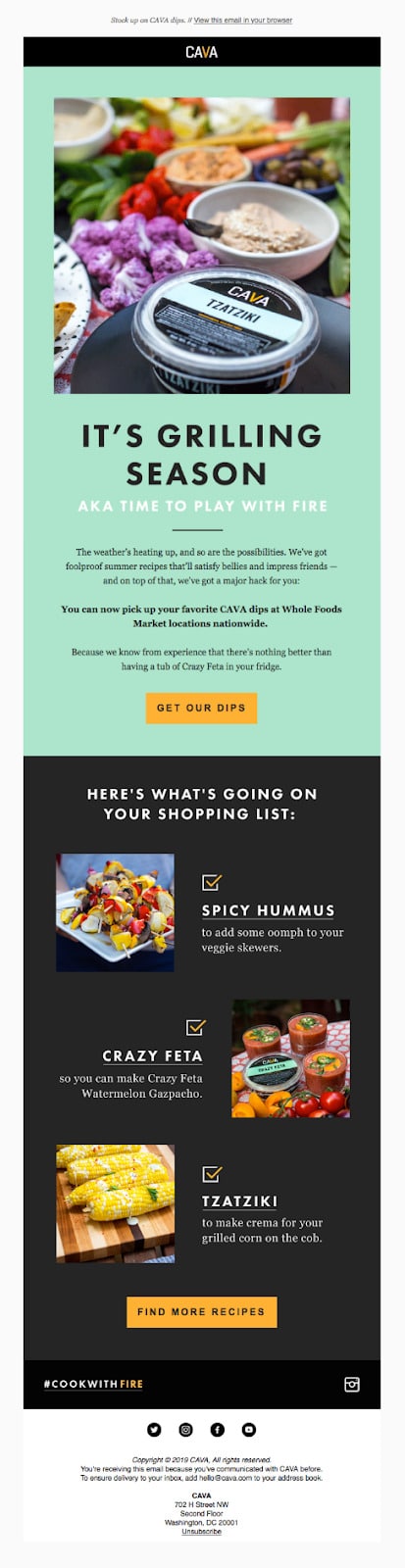
Fonte: e-mail davvero buone
Sebbene serif sia l'ideale per e-mail più lunghe, l'utilizzo di un font sans serif è comunque leggibile e accettabile. Con una sola riga di corpo del testo, Cater 2 Me ha inchiodato il design del loro font web. Confeziona un pugno e va dritto al punto senza distrarre.
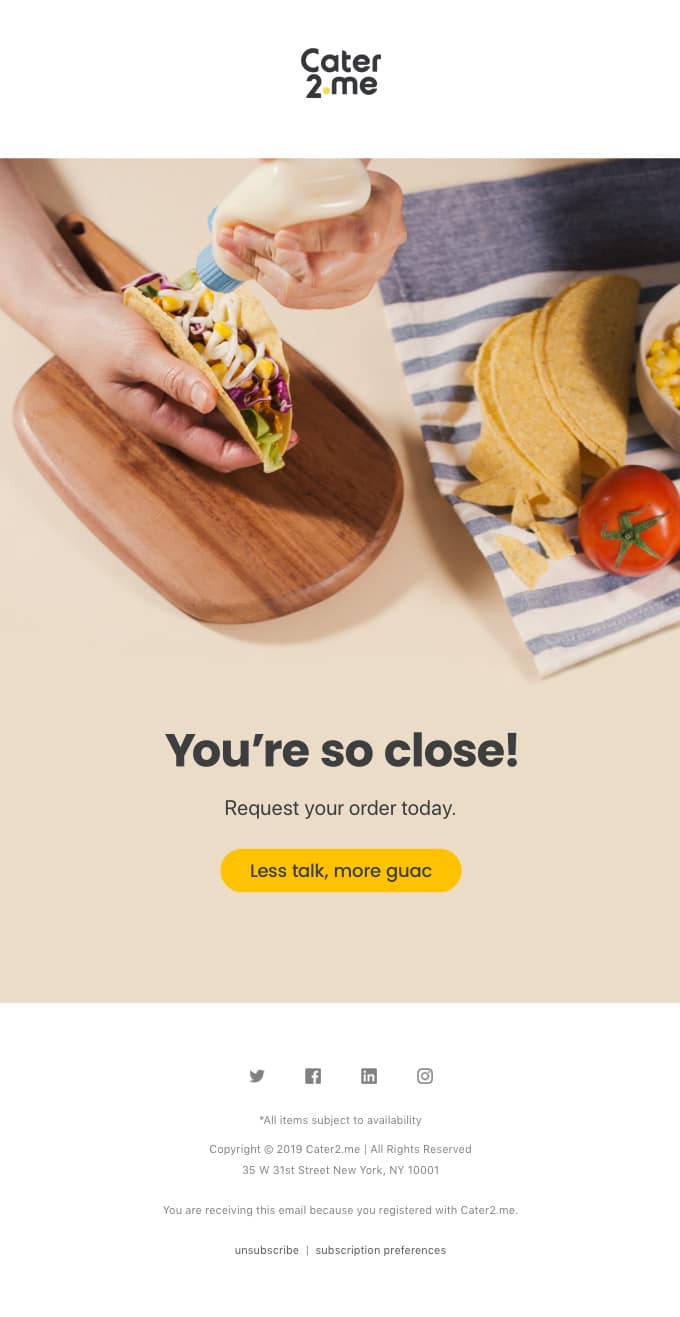
Fonte: e-mail davvero buone
2. Utilizzare un'intestazione stilizzata con un carattere del corpo accoppiato.
Sebbene possa sembrare più "semplice", l'utilizzo dello stesso carattere per l'intestazione e il corpo aiuterà a stabilire una migliore identità del marchio e garantire che l'intero messaggio venga visualizzato nel client di posta elettronica. Quando sviluppi la tua e-mail, assicurati che l'intestazione e il corpo siano di dimensioni diverse e abbiano spazi interni e stili diversi per differenziare meglio tra i due. È anche importante notare che più font web hai, più tempo impiegherà il caricamento della tua e-mail, che è un altro vantaggio dell'utilizzo di un solo font.
Prendi questo esempio da Lululemon. L'azienda utilizza intestazioni che sono 2 volte il corpo del testo con un riempimento sufficiente tra i due. Gli abbonati possono facilmente distinguere tra i due elementi creando un design pulito e classico.
Fonte: e-mail davvero buone
Tuttavia, se vuoi essere più creativo, l'abbinamento di diversi tipi di carattere che si completano a vicenda può aiutarti a distinguerti nella posta in arrivo e coinvolgere gli abbonati. Si consiglia di utilizzare solo due caratteri Web per e-mail, ma può essere complicato perché non si desidera che i caratteri siano illeggibili e inaccessibili. Se stai cercando un modo per scoprire font comparabili, puoi utilizzare Font Pair per trovare l'abbinamento dei font più efficace per il tuo design di posta elettronica.
Tattly fa un ottimo lavoro nell'accoppiare due caratteri diversi, pur rimanendo in linea con gli standard del loro marchio. L'intestazione attira immediatamente la tua attenzione e attira i tuoi occhi sul corpo per vedere cosa comporta la vendita. A causa delle immagini, puoi dire che questo marchio è più spensierato, quindi i caratteri multipli funzionano.
Fonte: e-mail davvero buone
3. Creare una struttura dei caratteri coerente.
Dopo aver selezionato i caratteri web, hai molti altri elementi da considerare come la dimensione del carattere, la spaziatura, i collegamenti e i pulsanti, i colori e altro ancora. Queste funzionalità ti aiuteranno a mantenere le tue e-mail coerenti, indipendentemente dalla fase del percorso del cliente in cui si trovano i tuoi abbonati.
Carattere: per il corpo del testo, il tuo carattere dovrebbe avere una dimensione di 14px su desktop e 16px per dispositivi mobili. Quando utilizzi un design reattivo, verifica che i caratteri supportati dalla posta elettronica oscillino automaticamente tra le dimensioni dello schermo.
Spaziatura: in particolare tra l'intestazione e il corpo del testo, assicurati di avere un'altezza della linea ampia compresa tra 22 px e 24 px. Spazi troppo stretti possono ridurre la leggibilità e il coinvolgimento.
Collegamenti e pulsanti: durante la creazione di collegamenti e pulsanti, non utilizzare un carattere separato per sottolineare la frase principale e verificare se include il collegamento di ancoraggio. I pulsanti sono un ottimo modo stilizzato per attirare l'attenzione sul tuo invito all'azione.
Colori: usa solo tre colori che si identificano con gli standard del tuo marchio: un colore per l'intestazione, uno per il tuo corpo e l'ultimo per i tuoi link.
Incartare
Se stai pensando di utilizzare i caratteri web nelle tue campagne e-mail, ti diciamo di provarci! I caratteri Web sono un ottimo modo per affascinare il tuo pubblico e aiutare a trasformare i tuoi potenziali clienti in clienti con un design di posta elettronica di grande impatto. Quando scegli i tuoi caratteri supportati dalla posta elettronica, assicurati di:
Crea stack di font di backup
Utilizza uno stile di carattere serif
Accoppia il testo dell'intestazione con il corpo del testo
Sviluppa una struttura dei caratteri coerente per tutte le campagne future